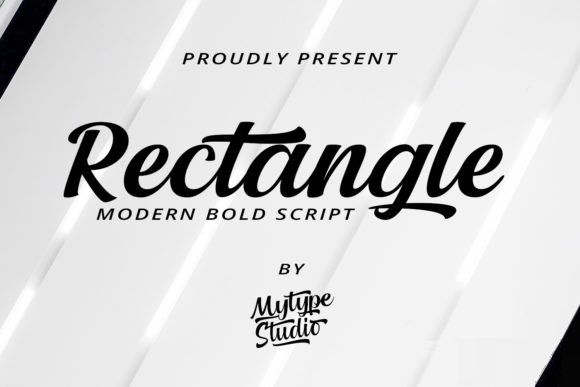
Название: Rectangle Font
Rectangle - это современный и смелый рукописный шрифт, созданный для придания стильности вашим заголовкам и логотипам.
Этот шрифт читается как сильный, уверенный и динамичный и может добавить тонны ностальгического характера в ваши проекты.
Название: Rectangle Font
Rectangle - это современный и смелый рукописный шрифт, созданный для придания стильности вашим заголовкам и логотипам.
Этот шрифт читается как сильный, уверенный и динамичный и может добавить тонны ностальгического характера в ваши проекты.